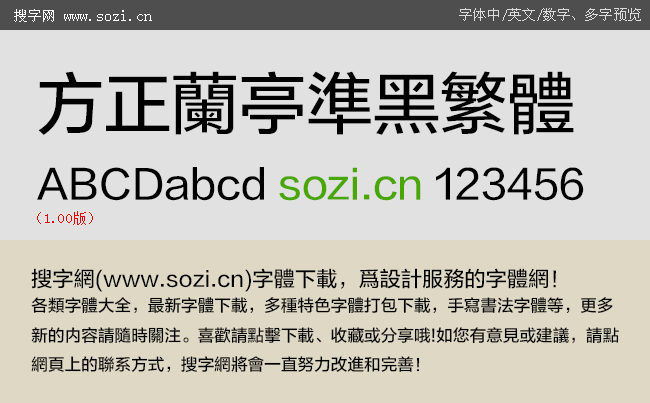
方正蘭亭準(zhǔn)黑繁體
搜字網(wǎng)提供一款方正蘭亭準(zhǔn)黑繁體下載,方正蘭亭準(zhǔn)黑體是一款比一般系統(tǒng)黑體粗的字體,該字體結(jié)構(gòu)優(yōu)美,識(shí)別性強(qiáng),端正大方,筆鋒粗曠,整體風(fēng)格出色,適用于廣告設(shè)計(jì)、名片設(shè)計(jì)、包裝印刷、產(chǎn)品設(shè)計(jì)等應(yīng)用。